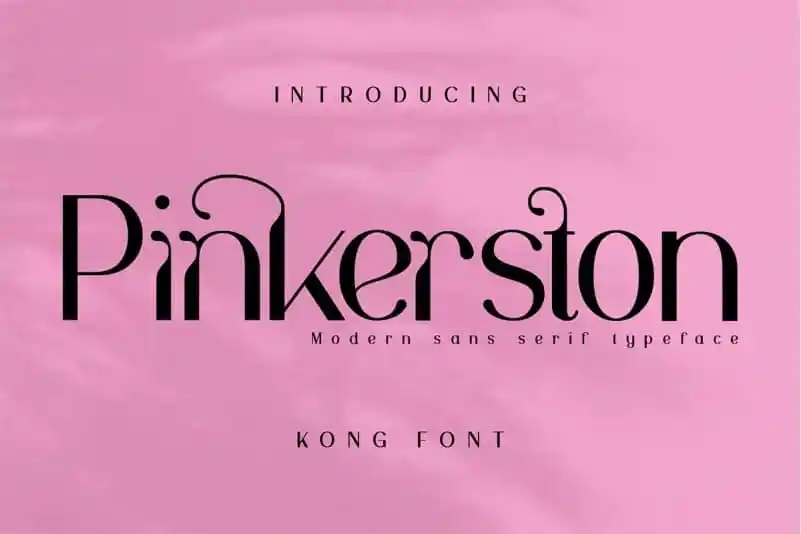
A Pinkerston Sans Serif Font é uma escolha perfeita para quem busca um estilo moderno e elegante que combina elementos vintage e serif. Esta fonte foi criada pelo talentoso designer fontkong na plataforma 99designs, oferecendo uma experiência de escrita completa com alternativas em maiúsculas e minúsculas cuidadosamente balanceadas para garantir um visual atraente e equilibrado. Com seu amplo leque de alternativas maiúsculas e minúsculas, essa fonte proporciona flexibilidade sem igual nas criações. Ideal tanto para headlines quanto para logos, esta elegante sans serif se destaca em uma variedade de formatos, incluindo postais, embalagens, camisetas, panfletos e muito mais. É perfeitamente adaptada para dar um toque único a seus projetos digitais ou impressos, tornando-a uma escolha inteligente para designers que valorizam tanto o estilo quanto a versatilidade de seu trabalho.